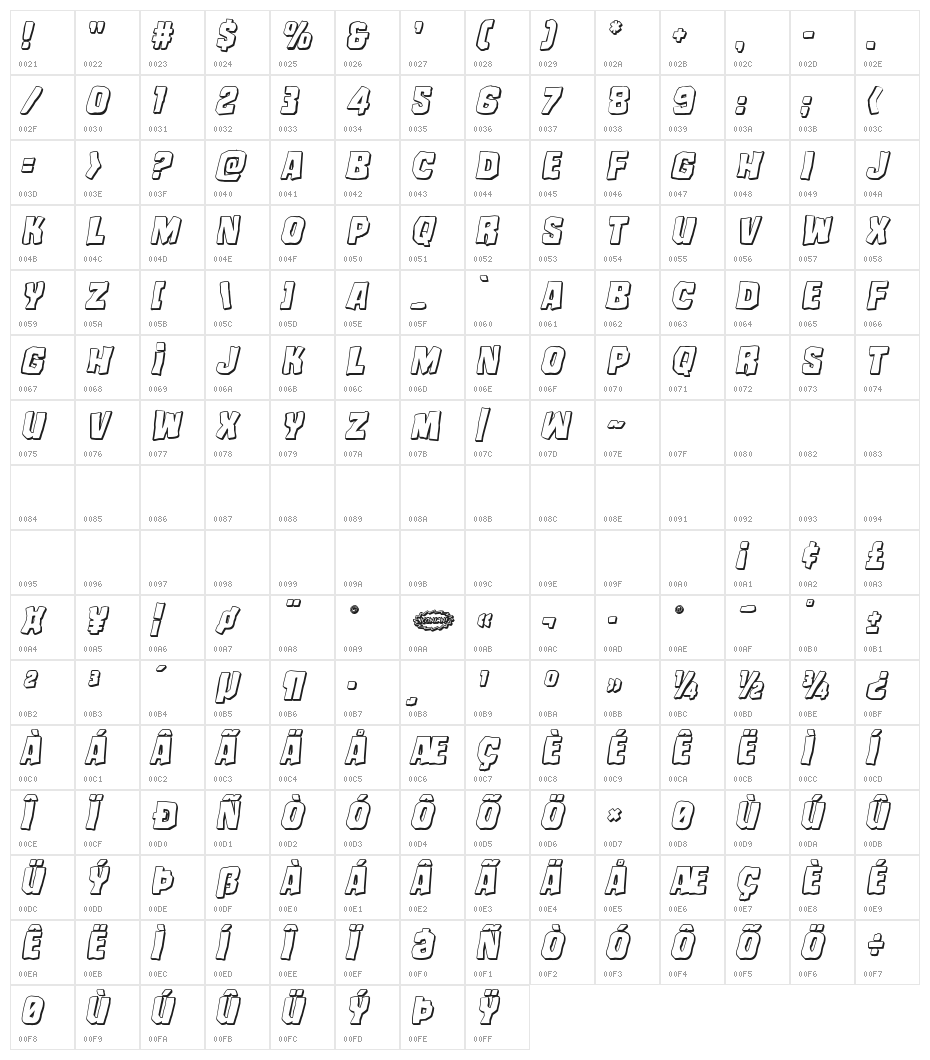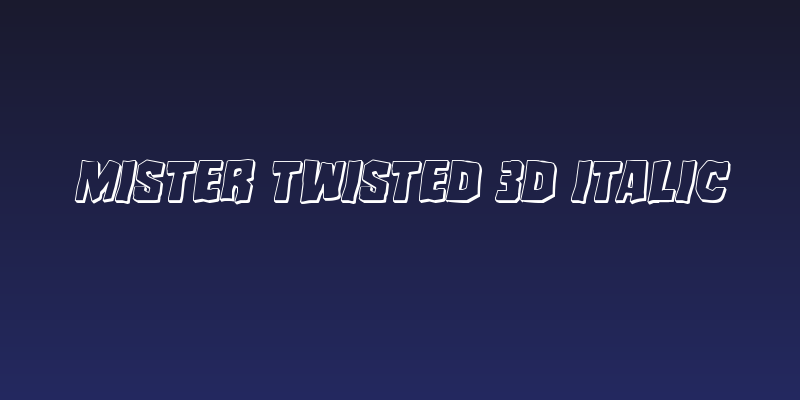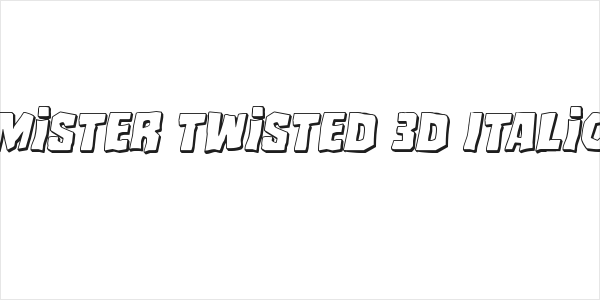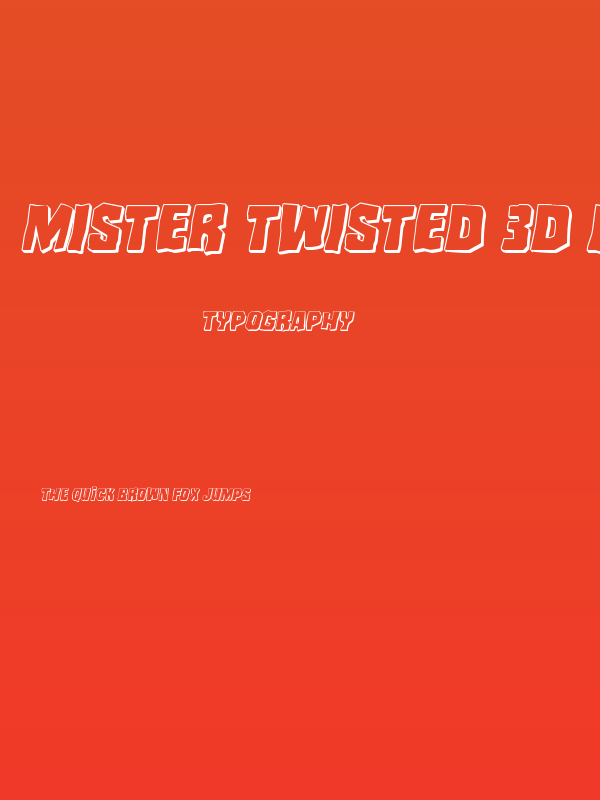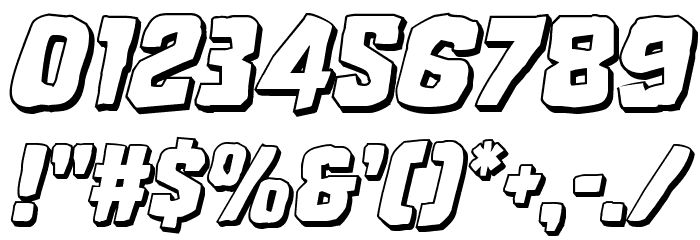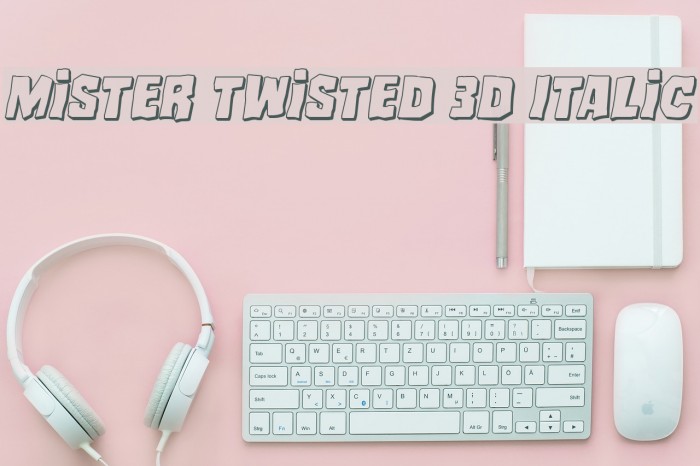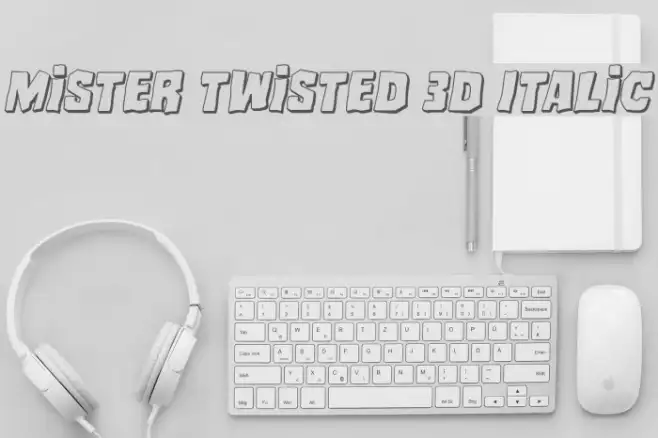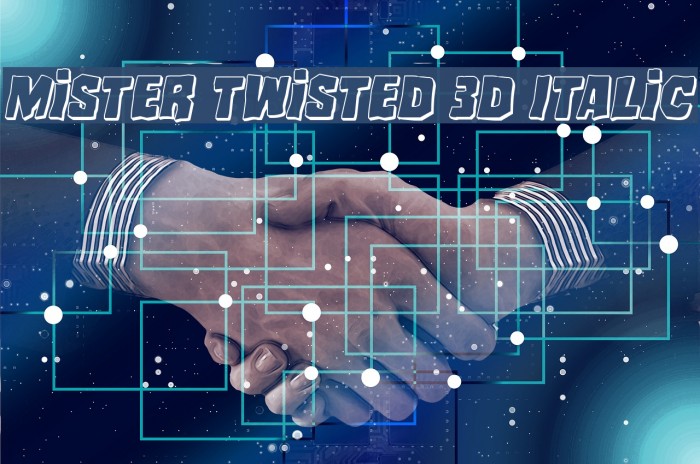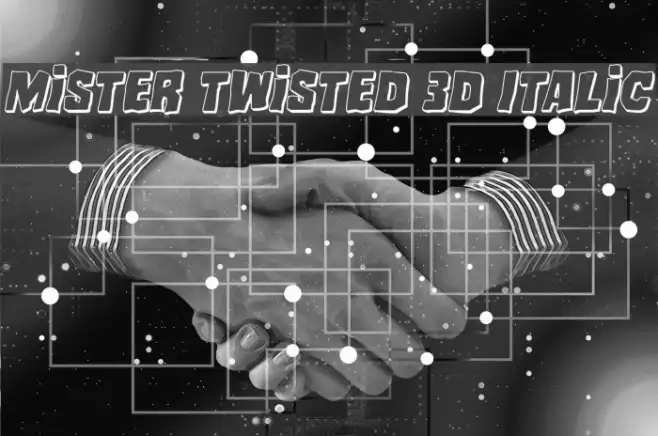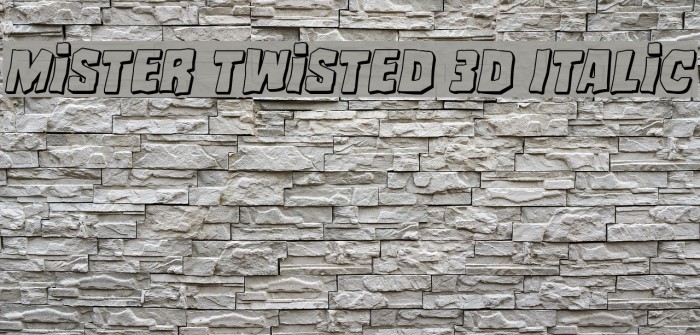
Mister Twisted 3D Italic Font
| Vorgeschlagene Projekte | Ideal for comic book titles, children's book covers, playful posters, and eye-catching advertisements. |